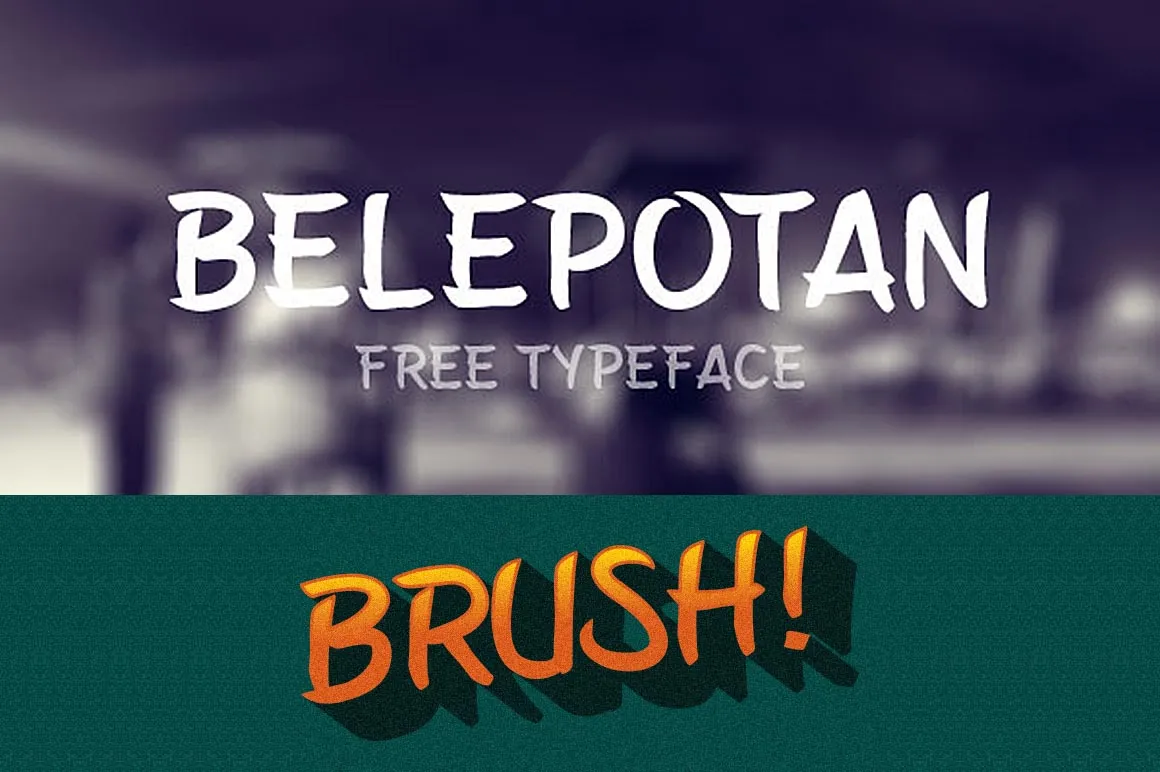
Belepotan Font
A fonte “Belepotan Font” é uma interessante escolha para aqueles que buscam expressar seu trabalho com estilo único e criativo. Especialmente adequada aos artistas digitais, arquitetos ou designers gráficos que desejam adicionar um toque personalizado a seus trabalhos, esta fonte customizada em brinquedo artesanal foi desenvolvida por Arwan Sutanto do Locomotype. Se você está procurando uma maneira de inovar seu estilo artístico e dar um toque autêntico às suas criações digitais, “Belepotan Font” é uma escolha ótima. Com sua natureza elegante e moderna, essa fonte Blackletter oferece um contraste interessante e único para qualquer projeto. Ela traz à tona a arte da escrita em uma forma ainda mais expressiva, permitindo que você transforme suas idéias em algo realmente especial. Seja em um design de website ou gráficos publicitários, essa fonte será uma ótima adição ao seu arsenal criativo. Não hesite em experimentar “Belepotan Font”. Esta fonte não apenas tornará seus trabalhos mais únicos, mas também o ajudará a expressar sua identidade visual de maneira ainda mais poderosa. Sinta-se à vontade para explorá-la e descubra como essa font pode trazer uma nova profundidade e personalidade a suas criações digitais.